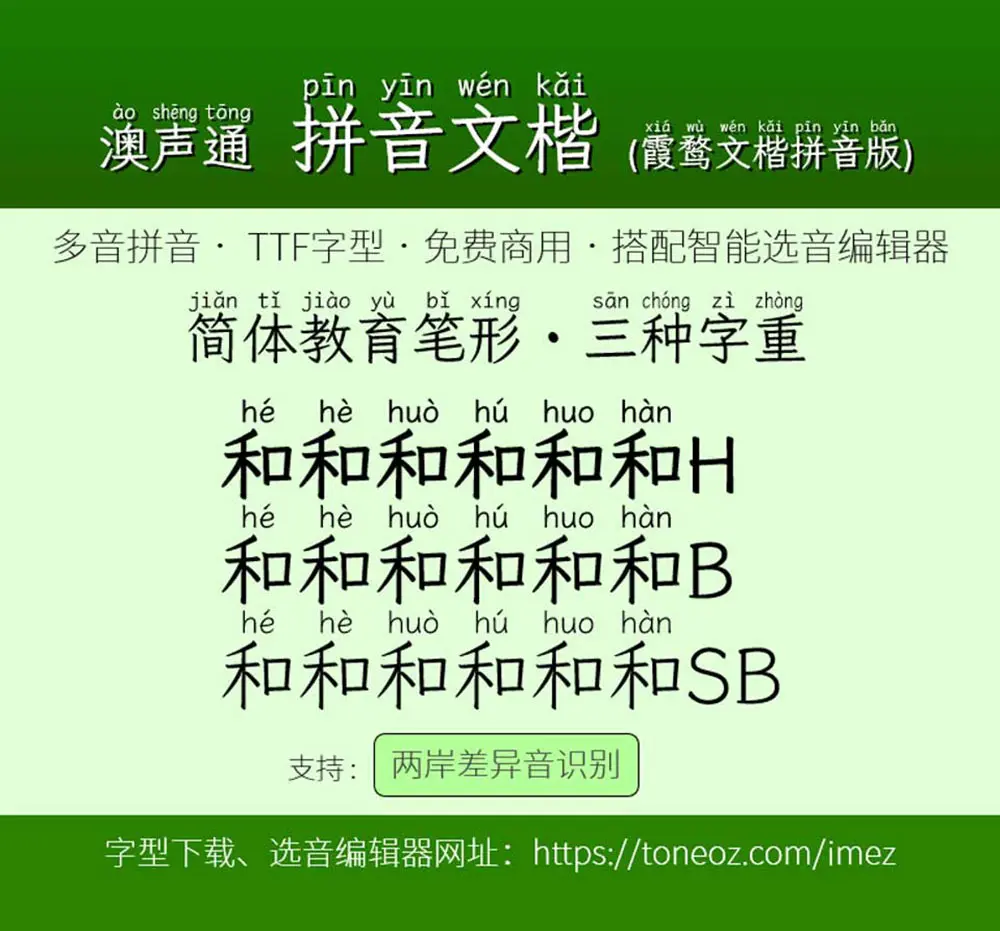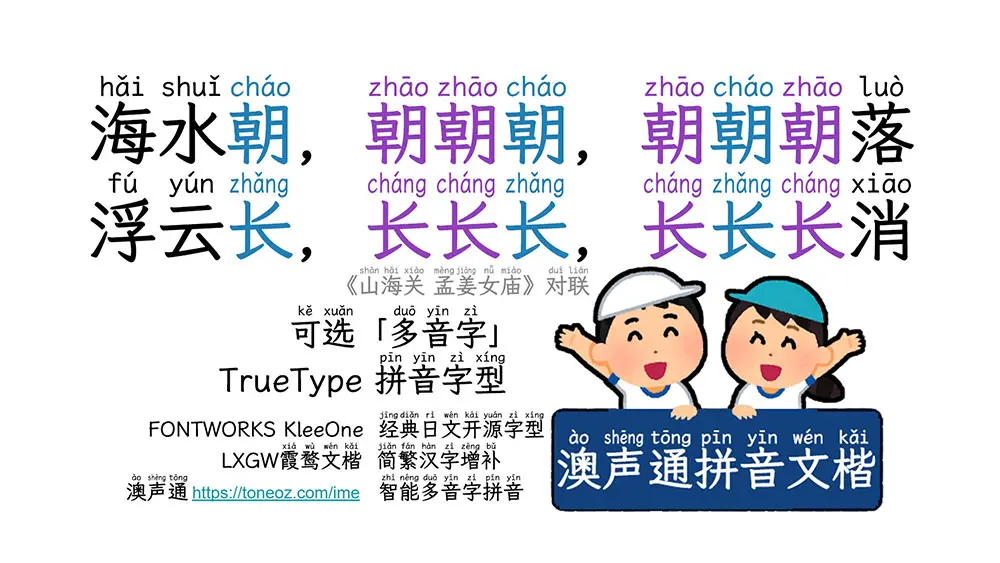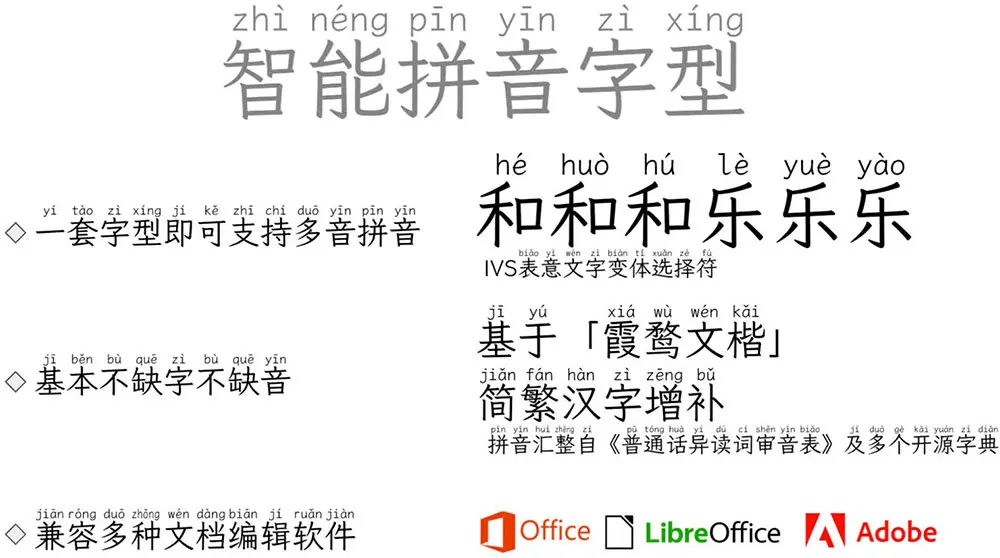
澳聲通拼音文楷預覽
澳聲通拼音文楷介紹
澳聲通拼音文楷該字體基於Fontworks的Klee One字體和LXGW的霞鶩文楷字體,用於添加簡體中文和繁體中文字形。拼音字符是由ToneOZ.com使用開源工具Mengshen添加的,其IVS異名字體概念來自But Ko的注音IVS。
可選多音字的TrueType拼音字型,可免費商用。搭配「免費免安裝」在線選音工具(IVS選音編輯器):https://toneoz.com/ime